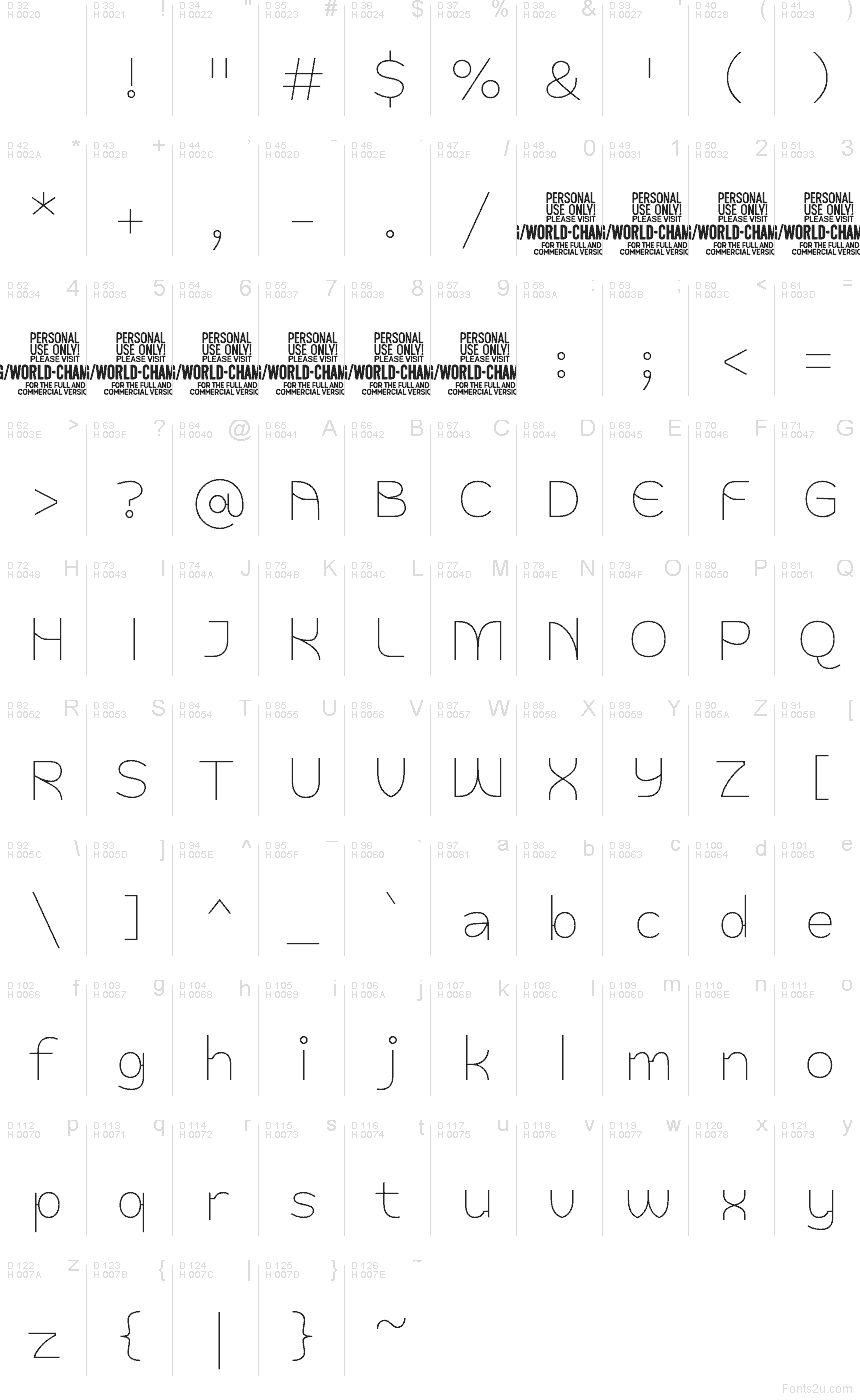
World Championship od Mans Greback AB je bezplatné Art Nouveau písmo, které dýchá nostalgií starých plakátů. Písmena jsou vykreslena jemnými tahy, širokými křivkami a několika teatrálními gesty, což tomuto písmu dodává vytříbený nádech počátku 20. století, spíše než tupý sportovní vzhled.
Skvěle se hodí pro branding barů a butiků, titulky časopisů, úvodní karty, obaly a grafiku událostí, kde pomůže trocha dobového dramatu. Jako bezplatné písmo se obzvláště hodí pro krátké nadpisy, loga a monogramy, protože ty protáhlé linie a kruhové tvary potřebují prostor, aby vynikly.